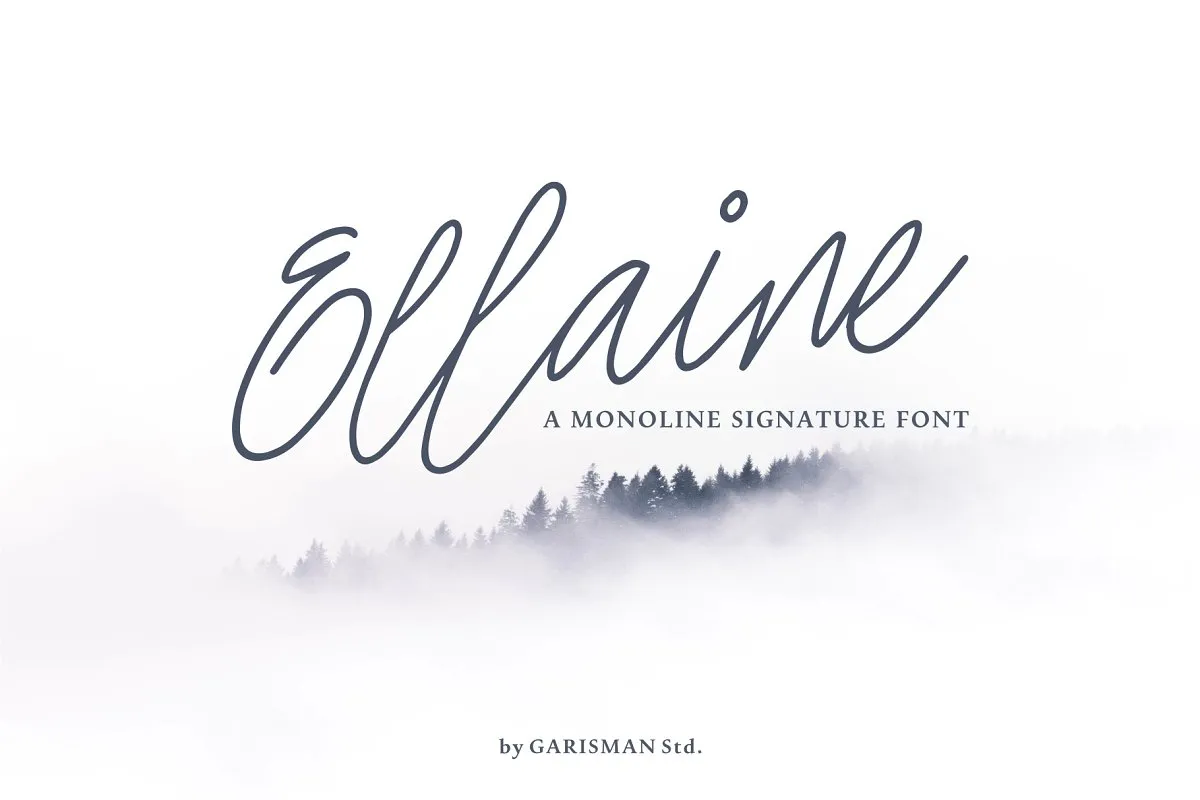
Ellaine Signature Font – Download Grátis
Olá, conheça a Ellaine Signature Font – uma nova fonte monolínea para assinatura, perfeitamente adequada para criar sua marca pessoal e projetos grandiosos. Introduzida pelo designer zziplex, esta font tem linhas elegantes que tornam ela perfeita para diversos usos. Seja criando logotipos, convites, embalagens de produtos, rótulos ou até mesmo postais de redes sociais e anúncios. A Ellaine Signature Font se adapta a todos esses campos, oferecendo uma aparição única e autêntica para sua marca. Experimente ela em seus próximos projetos e deixe seu design brilhar ainda mais!